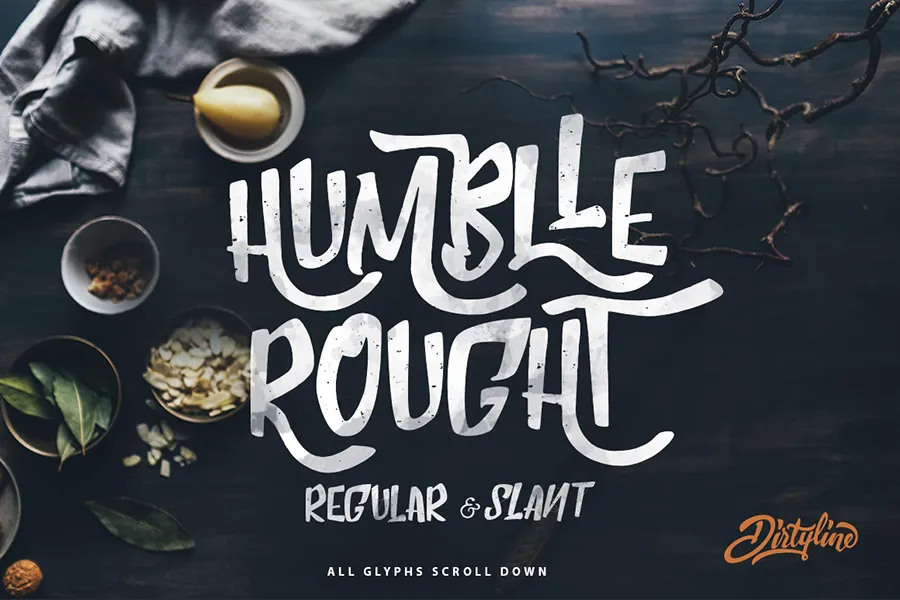
Humblle Rought Font – Download Grátis
A Humblle Rought é uma tipografia Brush moderna e vintage, criada com influências de Street Style e Lifestyle. Suas formas suaves e deslizantes capturam um estilo natural incrivelmente autêntico. Perfeito para uso em cartões de convite, cartazes, materiais de marca e até mesmo mensagens personalizadas, sua elegância se destaca nas mais diversas aplicações. Esta fonte bruta e quase imperfeita oferece uma aparência realista que transmite um ar autêntico e confiável, tornando-a perfeita para trabalhos profissionais e de identidade visual. Não espere a perfeição em todas as linhas desta fonte; seu estilo único é o que torna cada impressão única e autêntica.